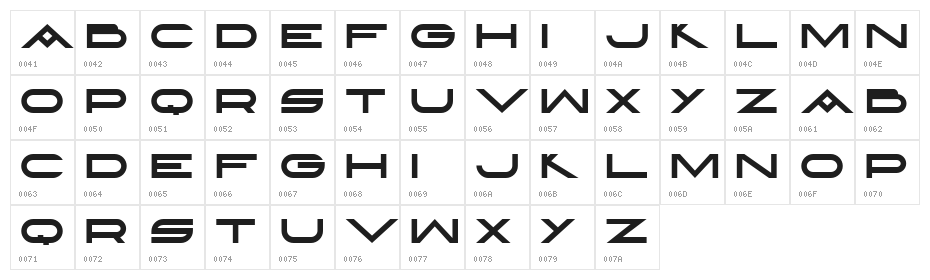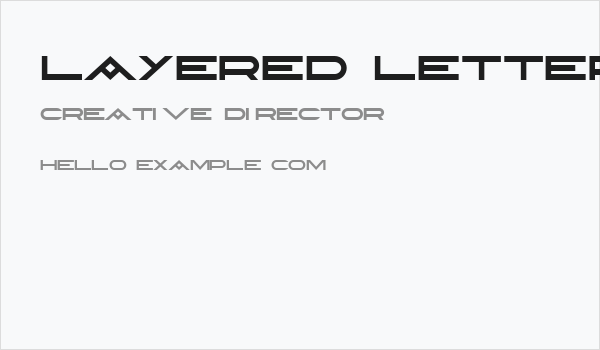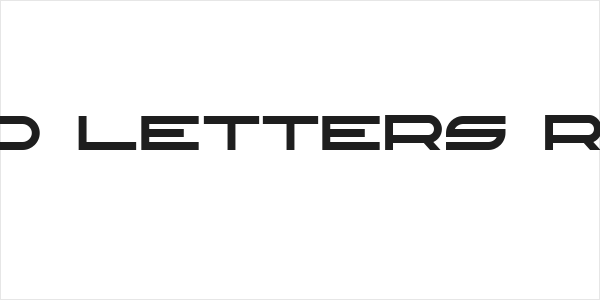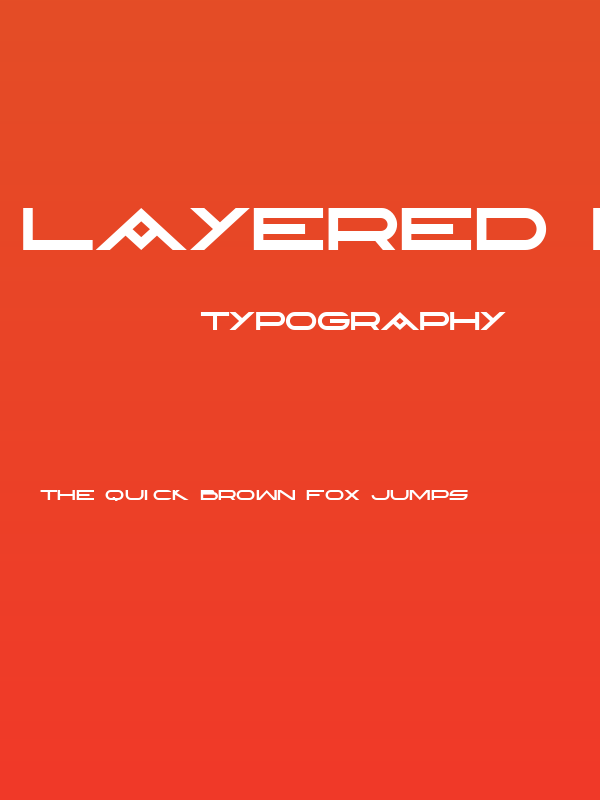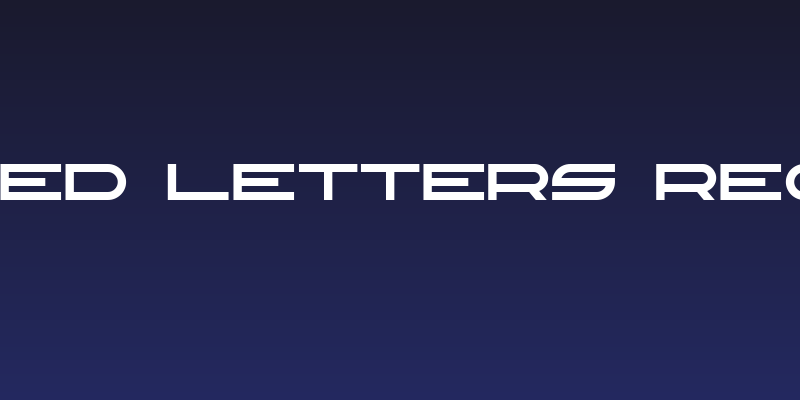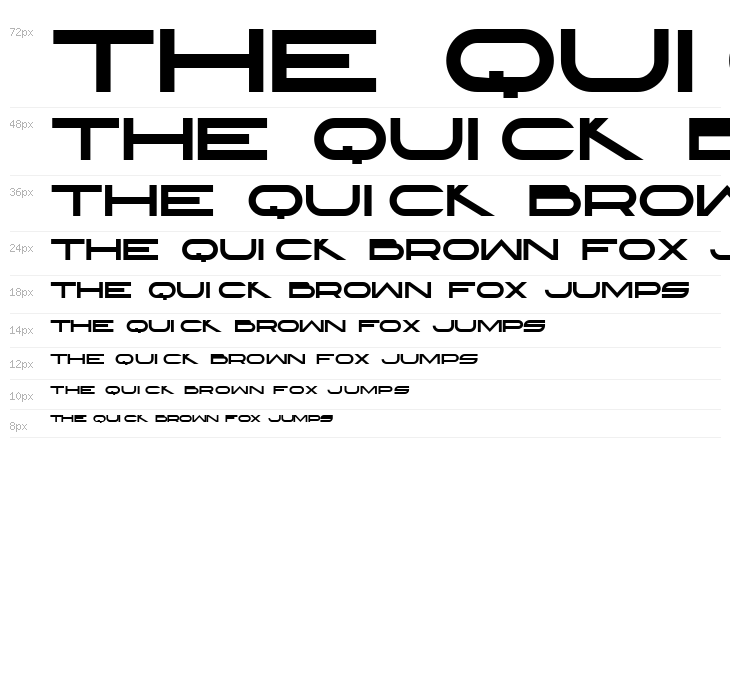
Layered Letters Regular Font
| Progetti proposti | Ideal for branding, logos, posters, and any design project that requires a futuristic and dynamic look. |